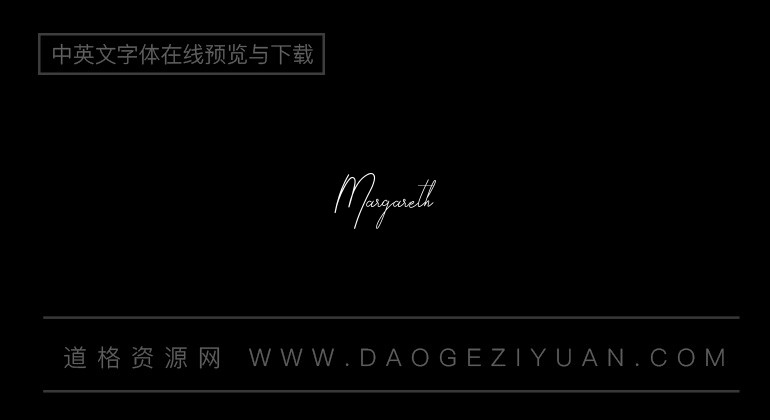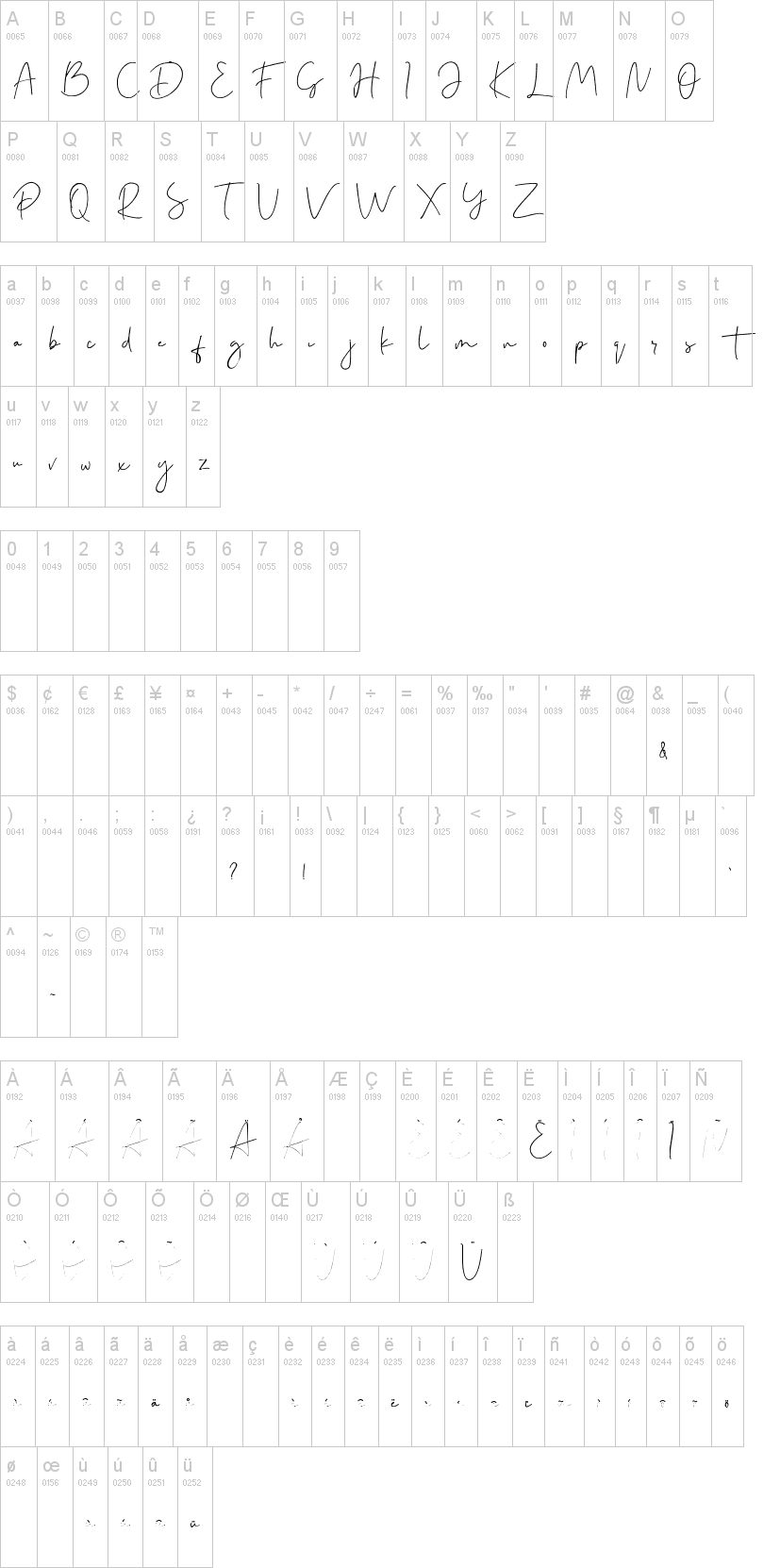
Margareth字体是一款极具艺术性的楷体字体,它由著名字体设计师Margareth(玛格丽特)设计,采用温柔、细腻的线条,拥有优雅而精致的外观,是一款极具艺术性的楷体字体。它适用于各种文档,包括书籍、报纸、杂志等,可以为文字增添优雅的外观,给人以深刻的印象。内容介绍
Margareth是一款非常不错的手写艺术字体,具有很好的视觉感,适合于文化类的宣传设计、商业类品牌的广告和产品包装设计以及个性化文字排版等较多场景。